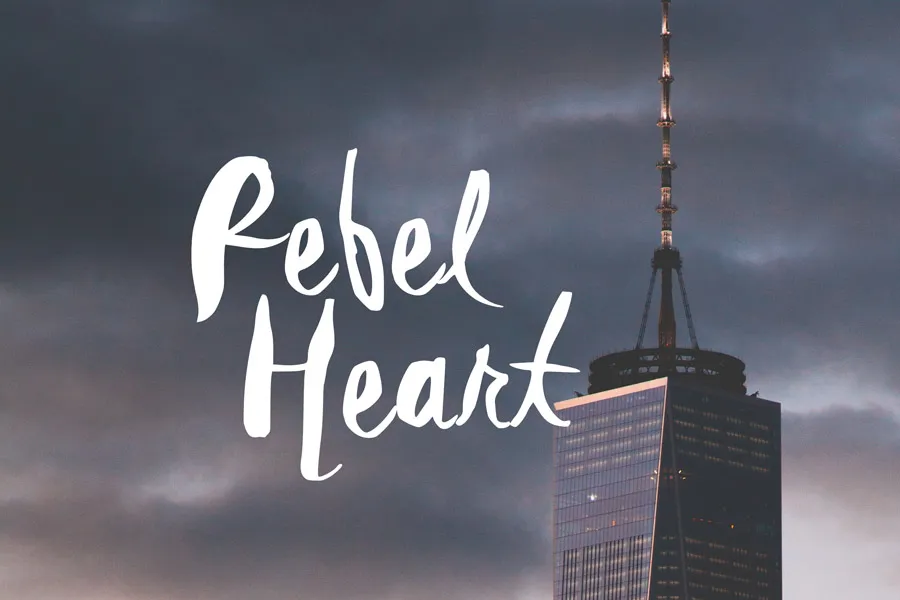
A ‘Rebel Heart’ é uma fonte livre que exibe o charme natural do traçado manual. Com suas letras bem-dribbadas irregularmente, ela tem a aparência de um traçado com canetinha. A ideia da designer Hamilton é proporcionar aos criadores de design algo leve e autêntico, sem precisões artificiais. Ideal para aqueles que buscam uma sensação mais natural em seus projetos digitais. Esta fonte permite dar uma cara única à sua arte digital, transformando cada letra num traçado com canetinha de verdade. Perfectly imperfect, ‘Rebel Heart’ é a escolha perfeita para quem busca um toque único e autêntico nos designs digitais.